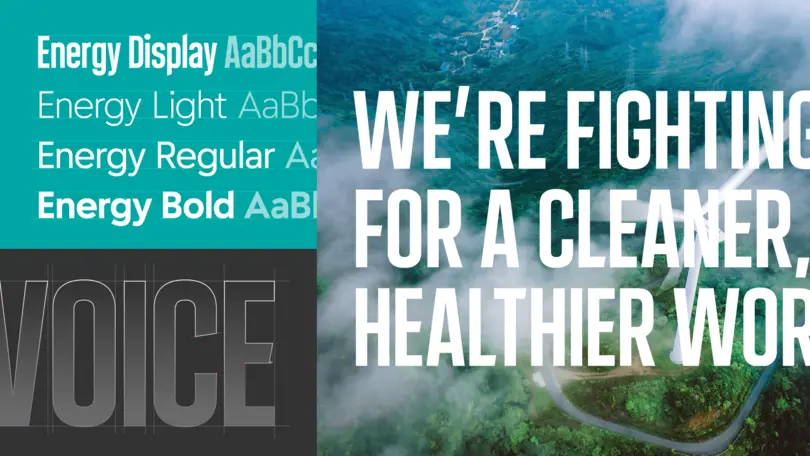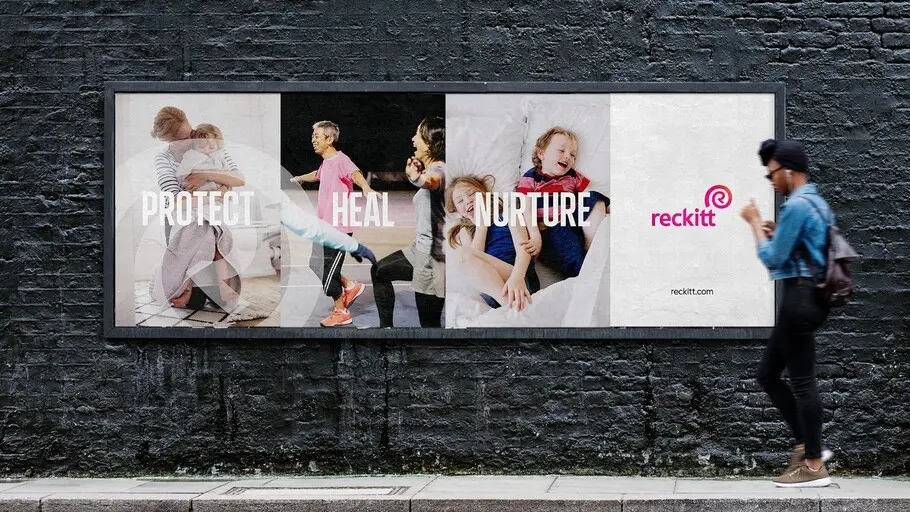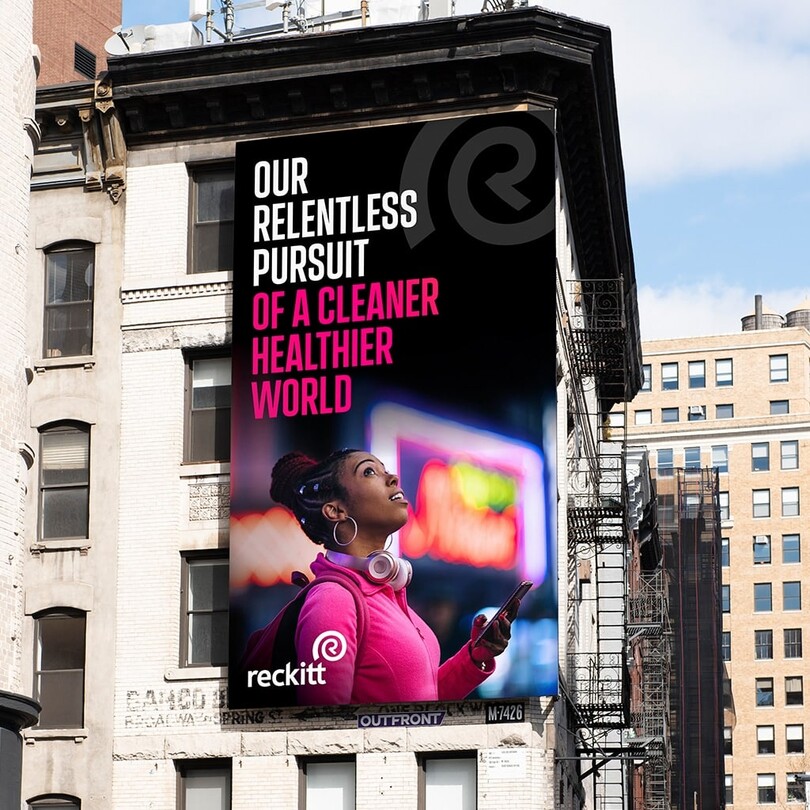
L’importance de la typographie dans le rebranding de Reckitt.
Après avoir annoncé sa stratégie d’objectif pour le développement durable, Reckitt Benckiser a voulu témoigner de son processus de transformation. La marque s’est réinventée et a pris le nom de Reckitt. Une réponse active à un monde et une société en pleine évolution – et où les marques d’entreprise se voient réinterroger leur rôle.
Dès les premières étapes du renouvellement du design, Reckitt et Conran Design Group ont senti les réels avantages que représenterait une police créée sur mesure. Une typographie personnalisée confère un élément vraiment unique au ton de voix d’une marque. Elle peut la réaligner et renforcer toute sa personnalité. Lorsqu’elle est bien faite, une typographie sur mesure peut saisir l’essence de la marque et la déployer avec cohérence à travers chaque plateforme, langage, application.
Depuis le début, Conran et le Studio Monotype avaient une idée très claire de ce qu’ils voulaient réaliser avec ce projet. Conran, en particulier, avait une grande vision d’avenir et de ce qu’une véritable police personnalisée permettrait à son client.
En évoquant les premières idées du Studio Monotype, tout le monde est tombé d’accord pour mettre l’accent sur la polyvalence et la simplicité au sein de cette police. Il était nécessaire qu’elle véhicule ces valeurs à travers tous les points de contact client. Friedrich Althausen, designer typographique chez Monotype et responsable du projet, était très heureux de développer à la fois un style affichage et une famille texte.
Mettre en relation la police d’affichage étroite et reconnaissable avec la famille texte hautement lisible a certes été un défi, mais c’est au final ce qui a permis de pousser encore plus loin la personnalisation – et de faire naître la police sur mesure de Reckitt.
Friedrich Althausen, designer typographique chez Monotype.
Grâce à la nouvelle police de Reckitt, la marque sera reconnue pour sa prouesse typographique. Dans un monde d’accélération numérique, une police forte devient bien plus qu’un simple actif de marque – elle le transcende pour devenir forme, message et véhiculer tout cela en soi.